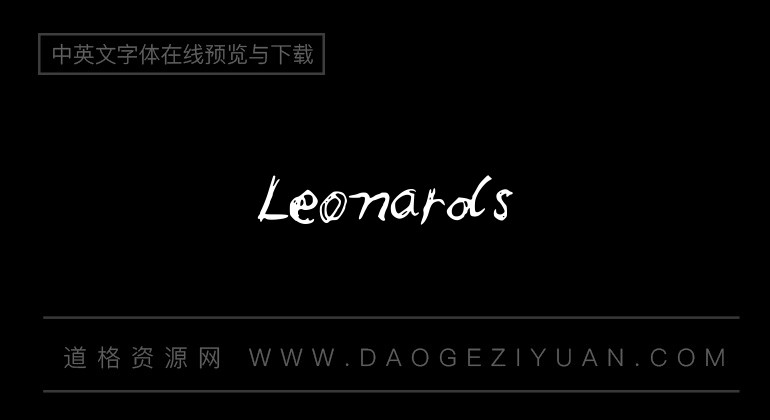
Leonards
Leonards 字体是一种比较特殊的字体,它的特点是文字的线条更加细腻,更加柔和,使得文字看起来更加立体,更有层次感。它的字体结构也比较特殊,可以更好地表达文字的细节。Leonards 字体适用于文字排版,可以使文字更加精致美观,更加有质感。
Leonards是一款非常不错的手写艺术字体,具有很好的视觉感,适合于文化类的宣传设计、商业类品牌的广告和产品包装设计以及个性化文字排版等较多场景。